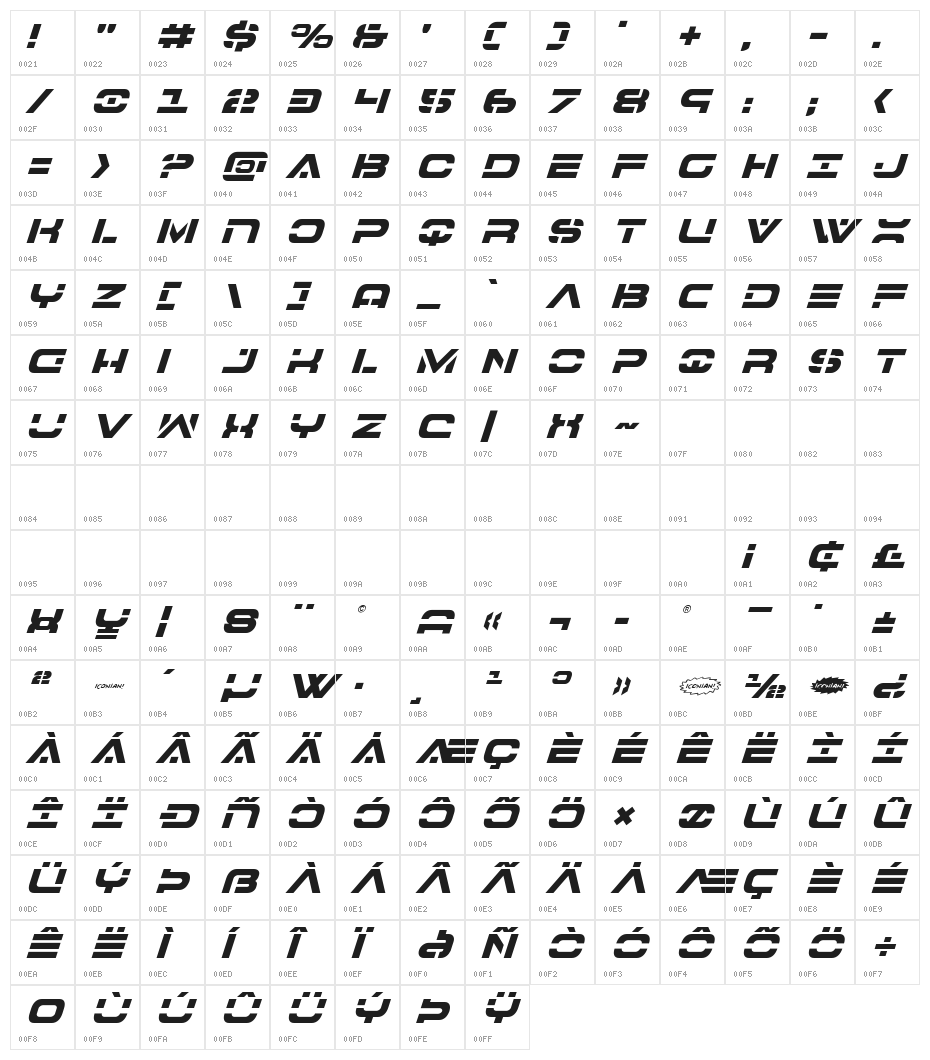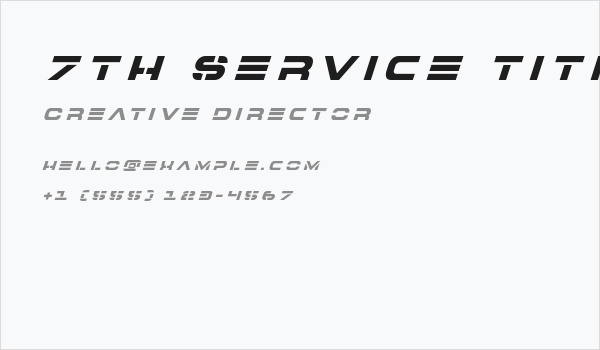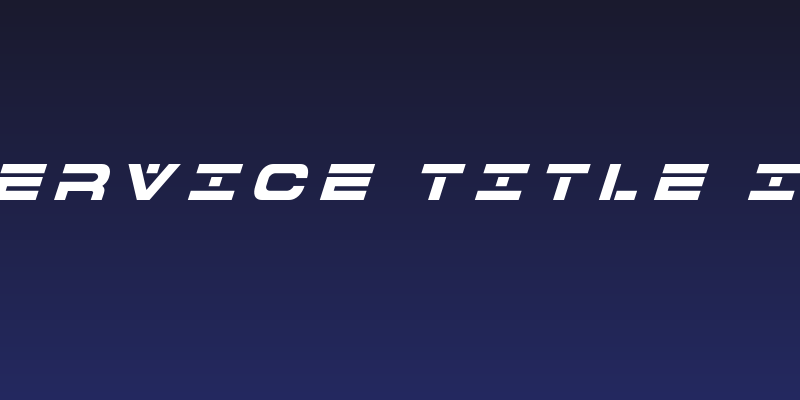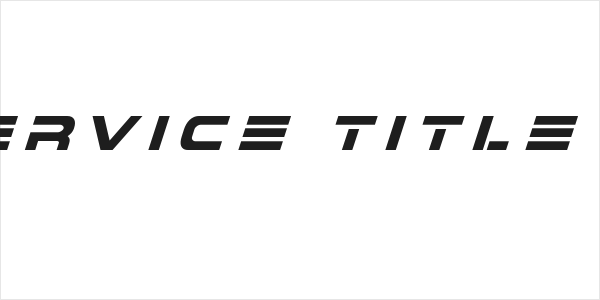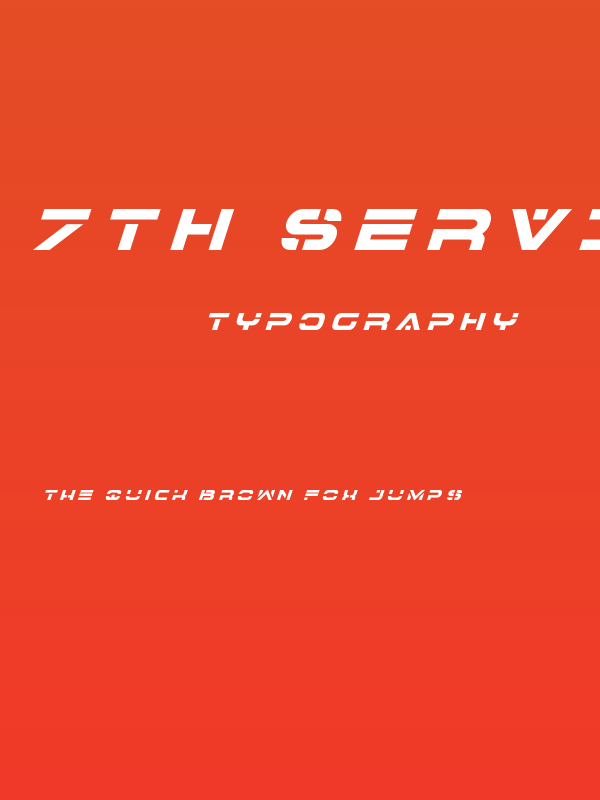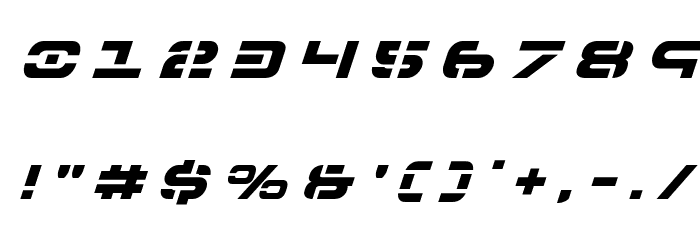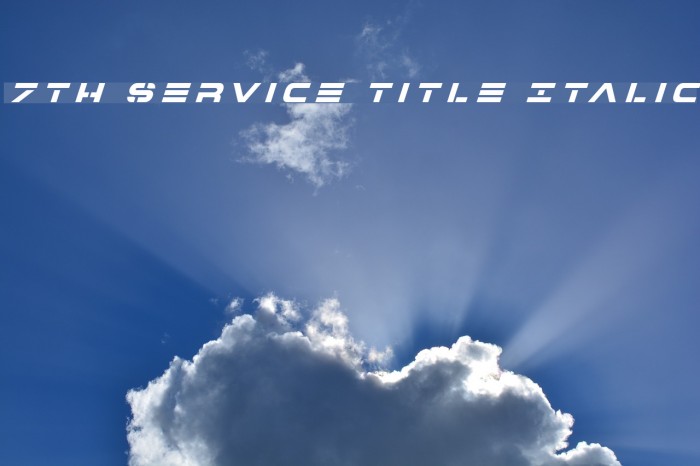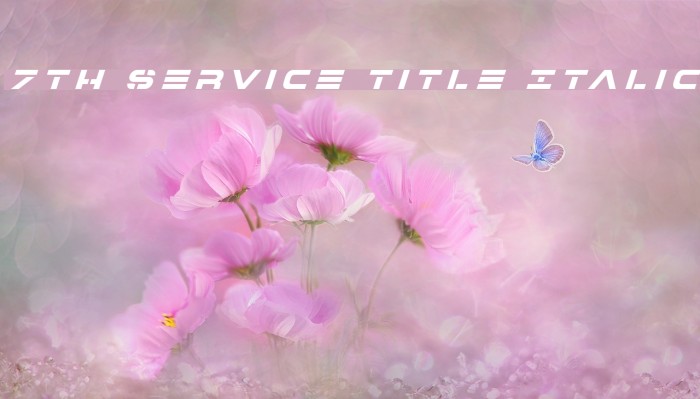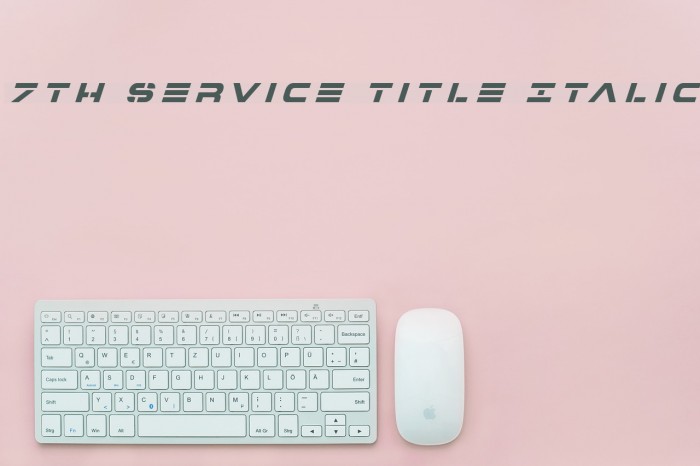
7th Service Title Italic Font
| Proyectos propuestos | Ideal for technology branding, sci-fi movie posters, video game titles, and modern advertising campaigns. |